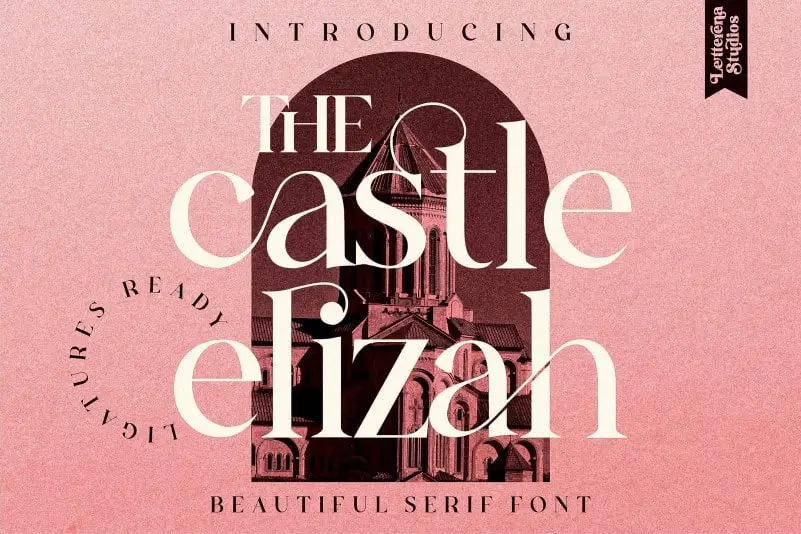
The Castle Elizah Serif Font – Download Grátis
A fonte ‘The Castle Elizah Serif Font’ é uma escolha que vai encantar designers amantes do bom gosto e personalidade única. Ela traz a elegância inconfundível das fuentes serif, mas com um toque de modernidade e originalidade que dá vida ao seu projeto, tornando-o imbativelmente destacado entre outros. Este é o tipo de fonte perfeita para quem busca expressar individualidade em seus designes, seja através da elegância do texto ou pela personalização única dos detalhes mais sutis. A designer Letterenastudios criou esta fonte inspirada em elementos arquitetônicos clássicos, resultando num estilo que atinge uma atmosfera de sofisticação e confiança. Seja para contratos profissionais ou artigos literários, ‘The Castle Elizah Serif Font’ se destaca por sua personalidade e elegância, tornando-se um recurso gráfico indispensável para qualquer designer em busca de uma fonte única que ilumine o seu trabalho.